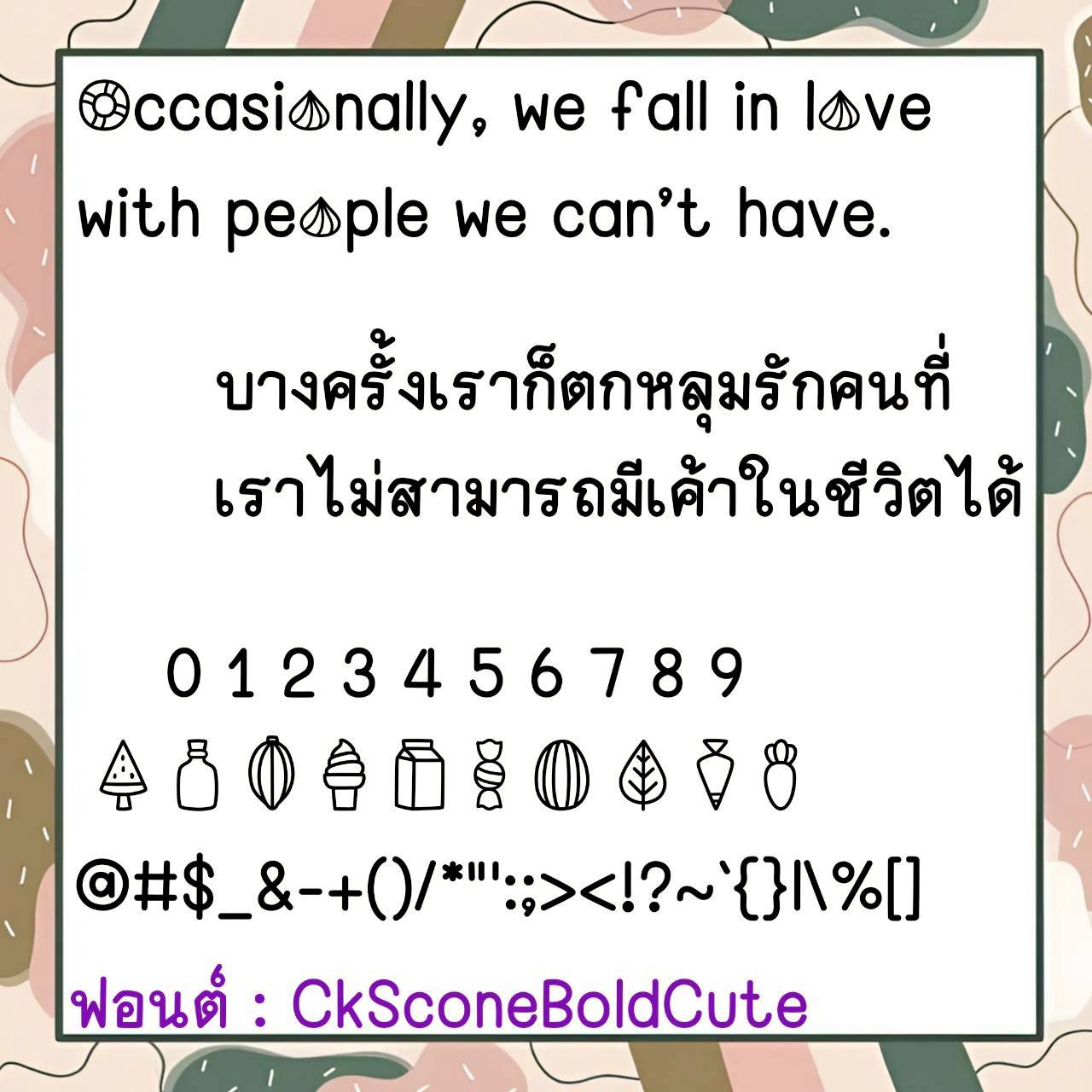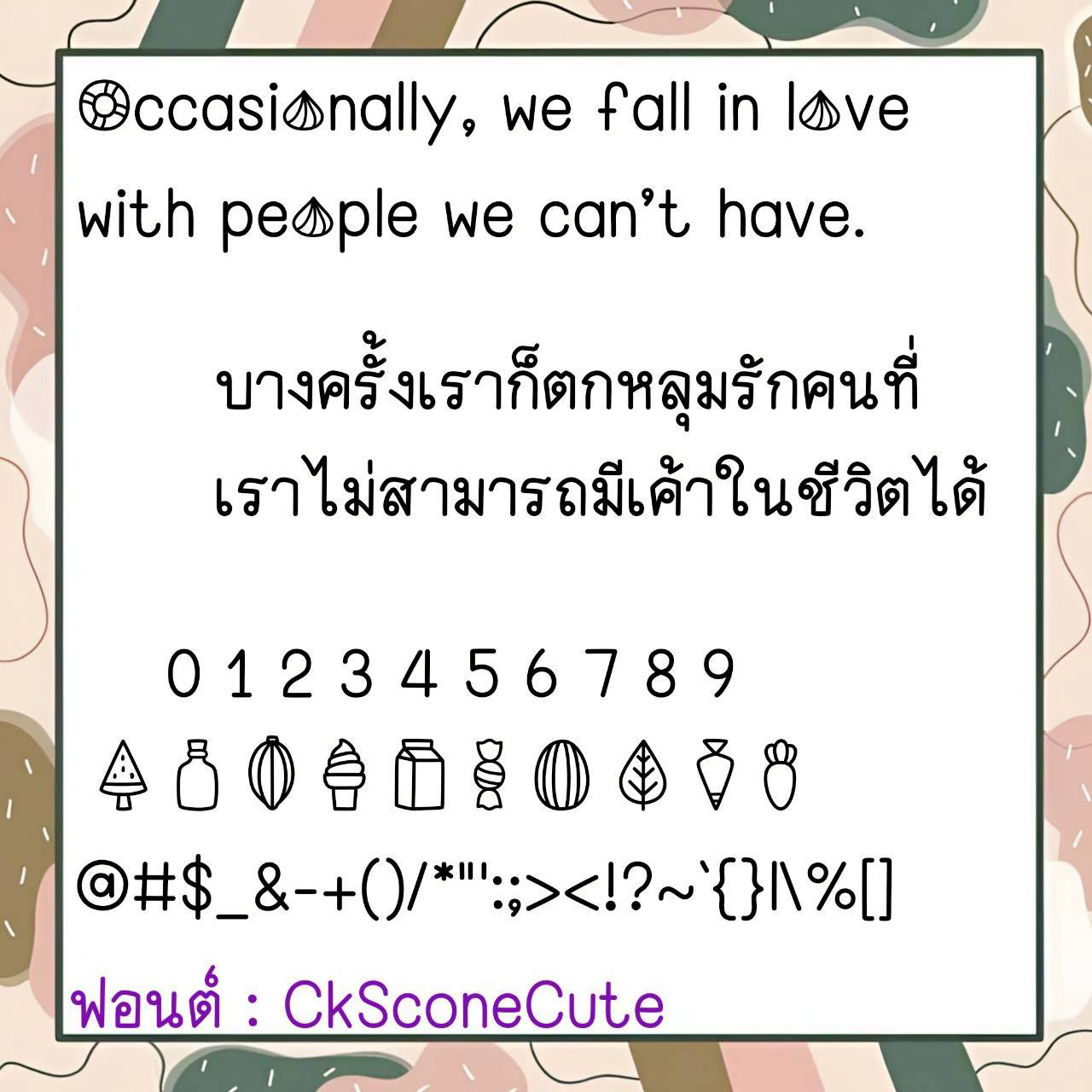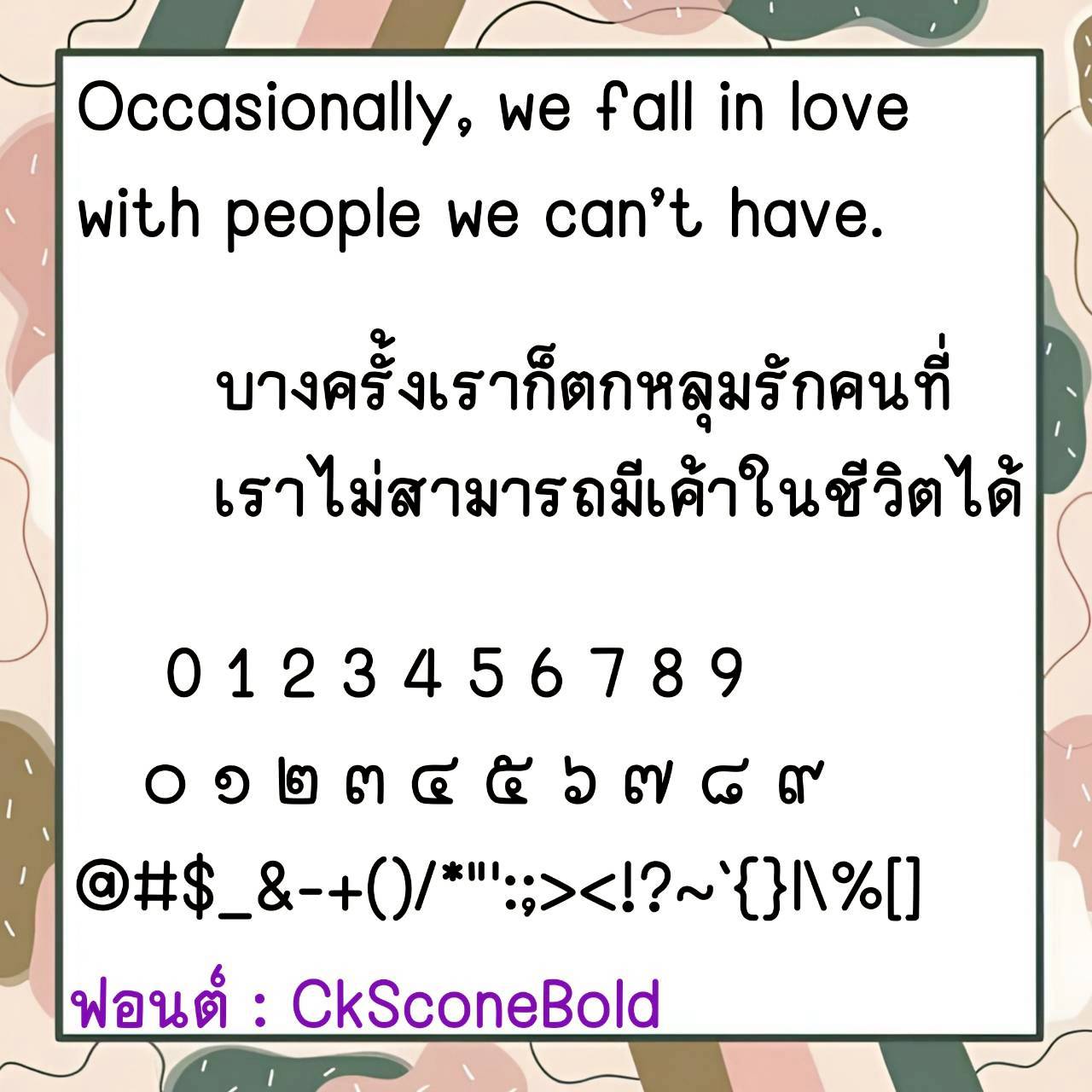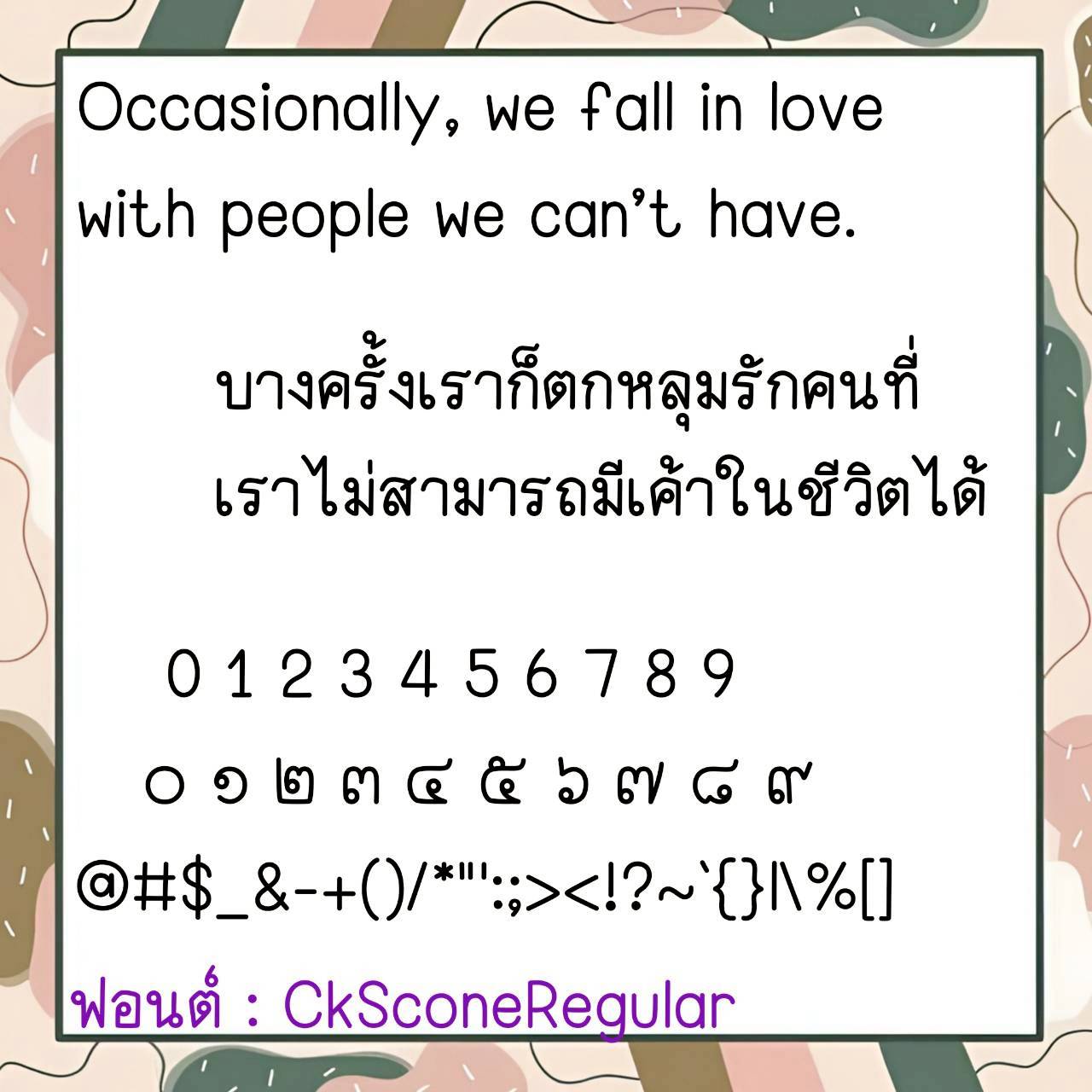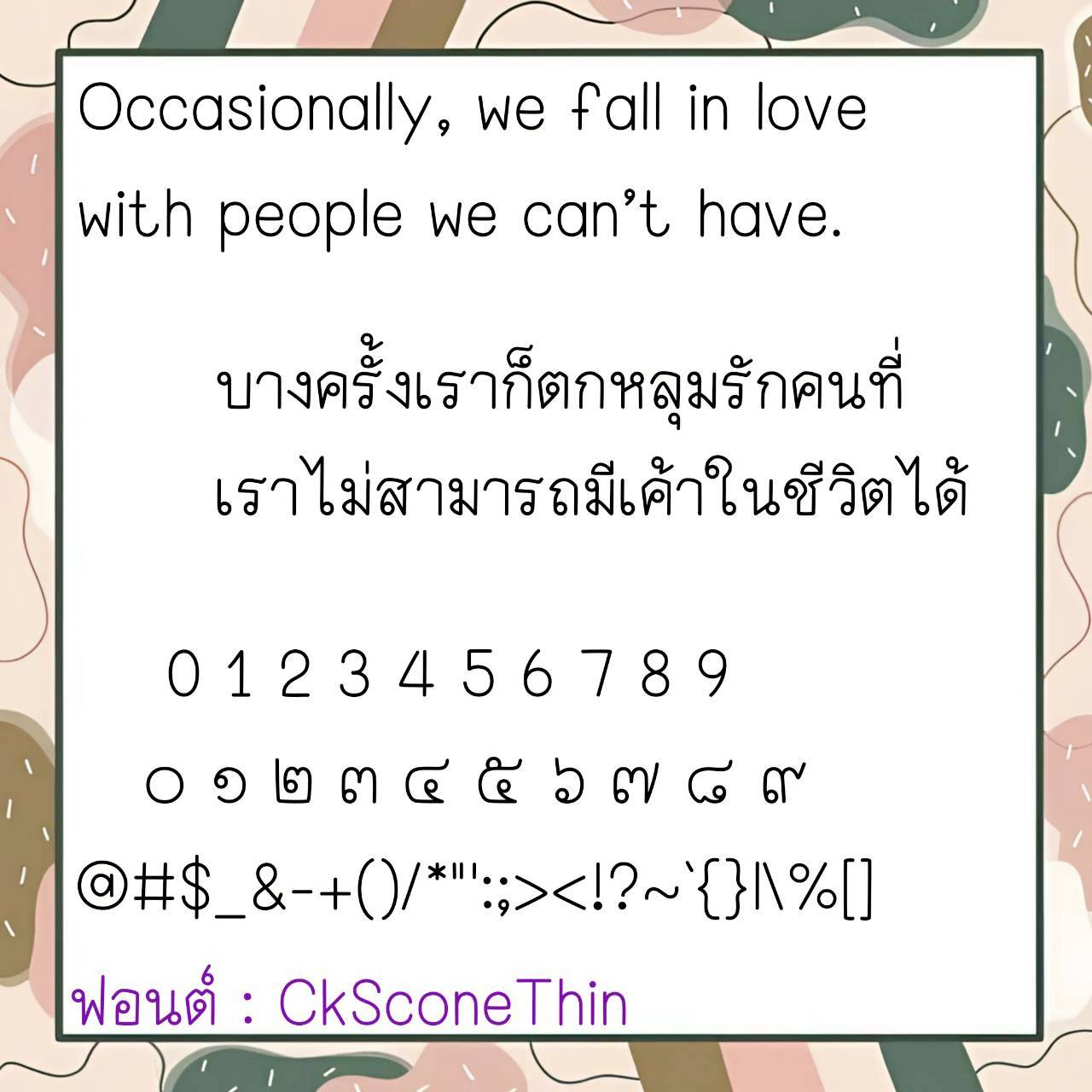
Font CkScone
ชื่อสินค้า : Font CkScone 💙
🔸 ฟอนต์ลายมือแนวตัวเหลี่ยมแบบไทย คล้ายการคัดลายมือ เน้นความเป็นระเบียบเรียบร้อย อ่านง่ายใช้งานง่าย และยังมีไฟล์อิโมจิน่ารักๆที่ใช้แทนเลขไทยให้ด้วยค่ะ 🥰💙
🔹 This Thai-style handwritten font features square characters, similar to calligraphy, emphasizing neatness, readability, and ease of use. It also includes cute emoji files to replace Thai numerals. 🥰💙